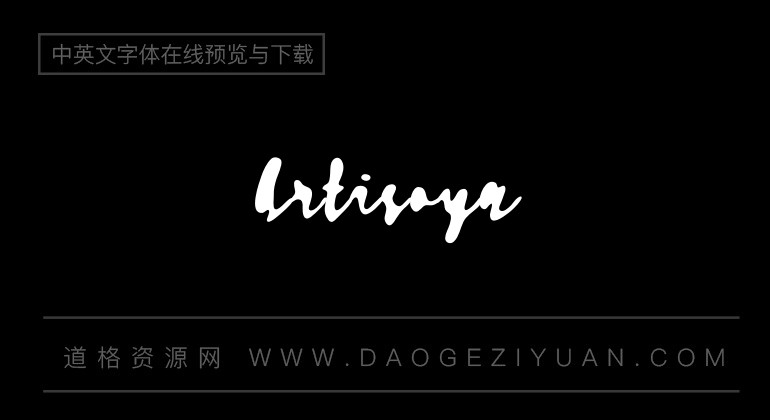
Artisoya 字体是一款由日本设计师渡边亮设计的字体,它采用了简洁的线条和清新的色彩,适合用于各种不同的设计风格。它的线条细腻,清晰,可以用来表达各种不同的情感,比如温柔、活力、清新、优雅等。它可以用于商业设计,也可以用于个人设计,比如海报、海报、卡片等。内容介绍
Artisoya是一款非常不错的手写艺术字体,具有很好的视觉感,适合于文化类的宣传设计、商业类品牌的广告和产品包装设计以及个性化文字排版等较多场景。